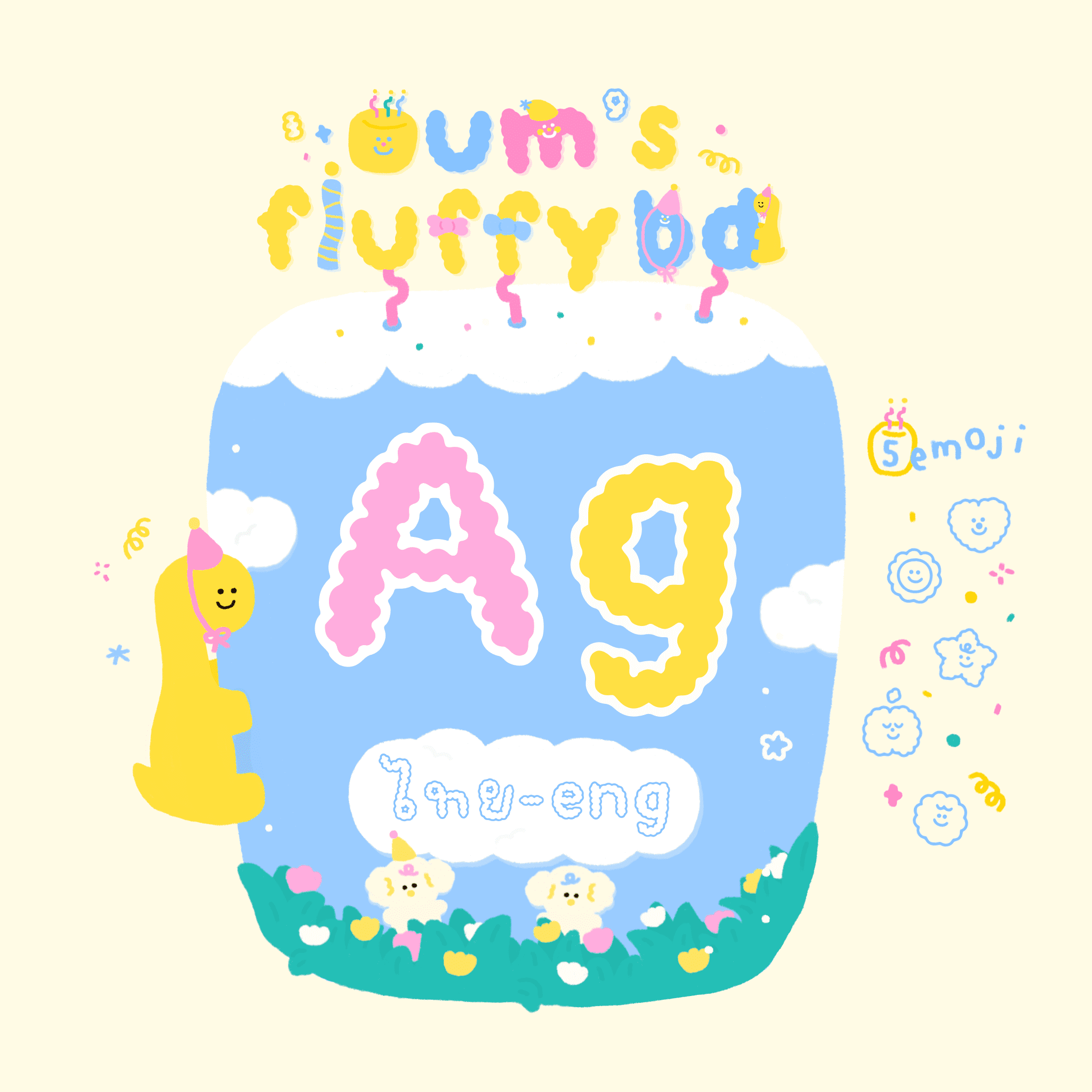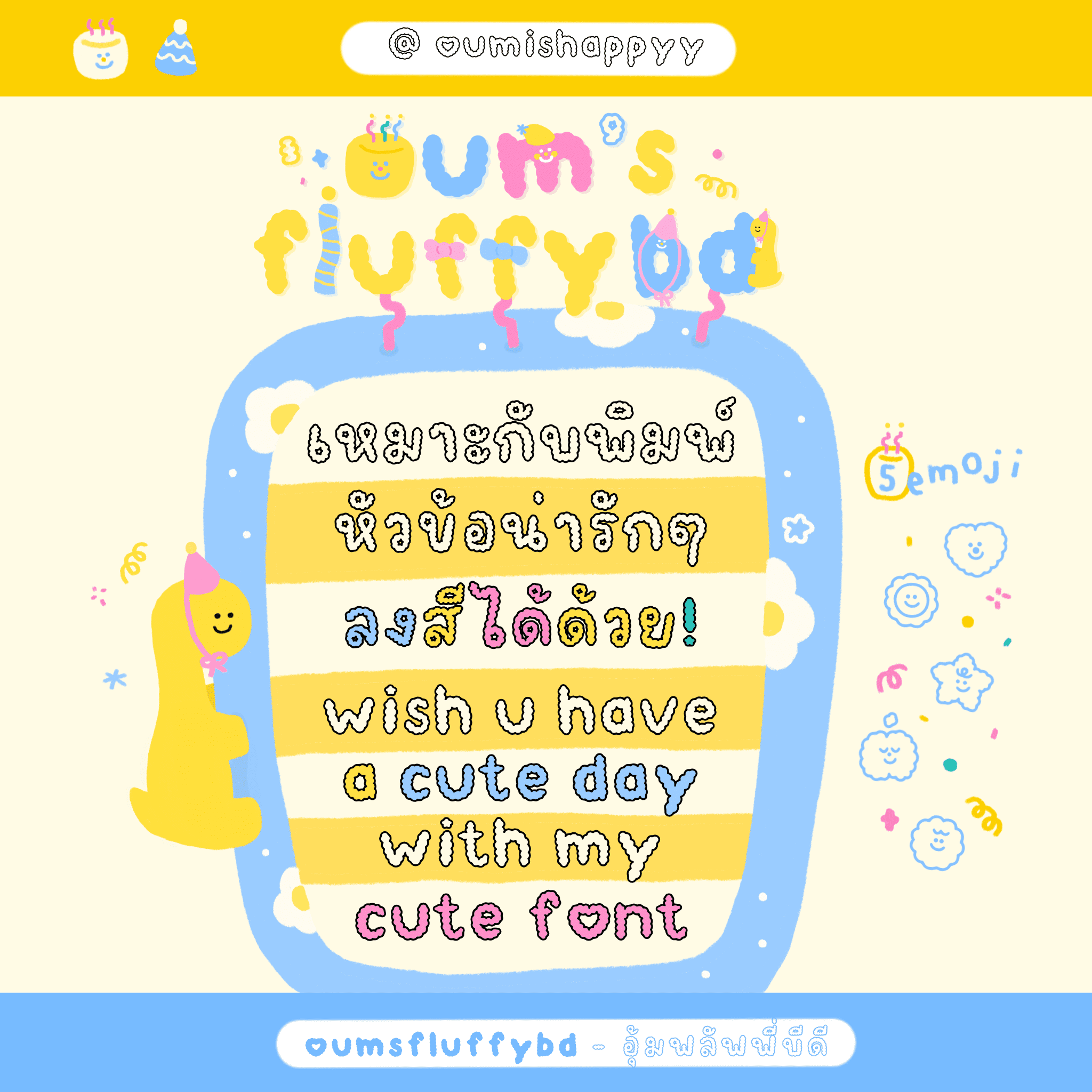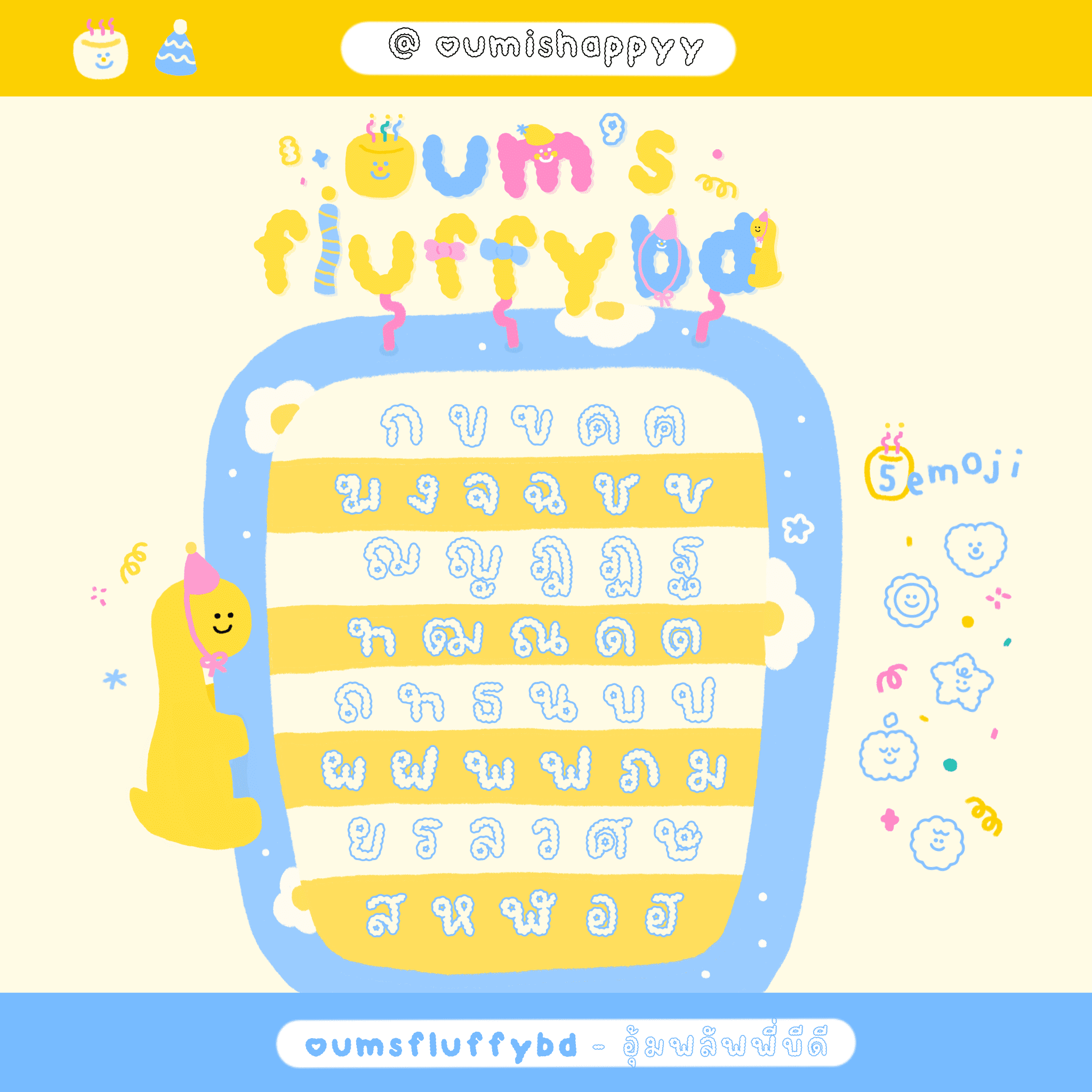
น้องเป็นฟอนต์ขอบปุกปุย ใช้พิมพ์หัวข้อก็คือแสนน่ารัก
ลงสีตกแต่งได้ด้วยเพิ่มความน่ารักนุ่มฟูอีก200% ☁️
⭐️ ความนุ่มฟูยังไม่หมดดด ยังมีน้องๆอิโมจิขอบปุกปุยให้ไปตกแต่งน่ารักๆอีก 5 แบบไปโลย ! (อยู่ที่เลขไทย๑-๕)